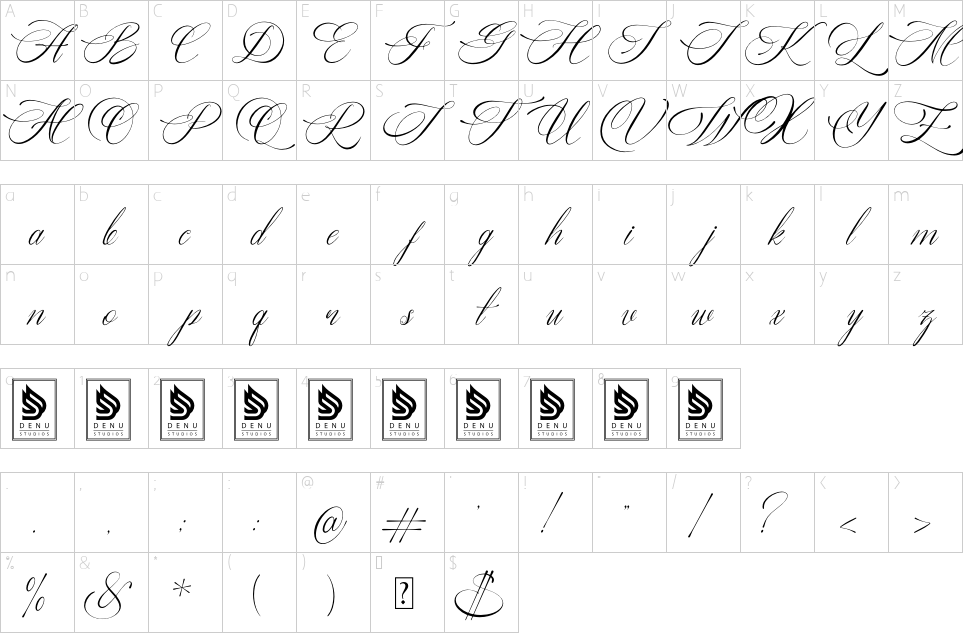
A fonte Marbelyn Walenstan é uma escolha agradável para designers gráficos e amantes da design, projetada pela Denustudios. Esta fonte está disponível gratuitamente tanto para Windows quanto para Mac, facilitando seu uso para um amplo espectro de usuários. Com sua design minimalista e elegante, a Marbelyn Walenstan é uma opção perfeita para aplicar em materiais de design, desde letras de banner até e-mail marketing, garantindo um visual atraente e profissional. Desenvolvida em 2023, a Marbelyn Walenstan já foi baixada mais de 819 vezes, evidenciando seu valor para designers que buscam uma fonte moderna e fácil de usar. Instale-a em seu computador agora e experimente a diferença que ela pode fazer em seu design.